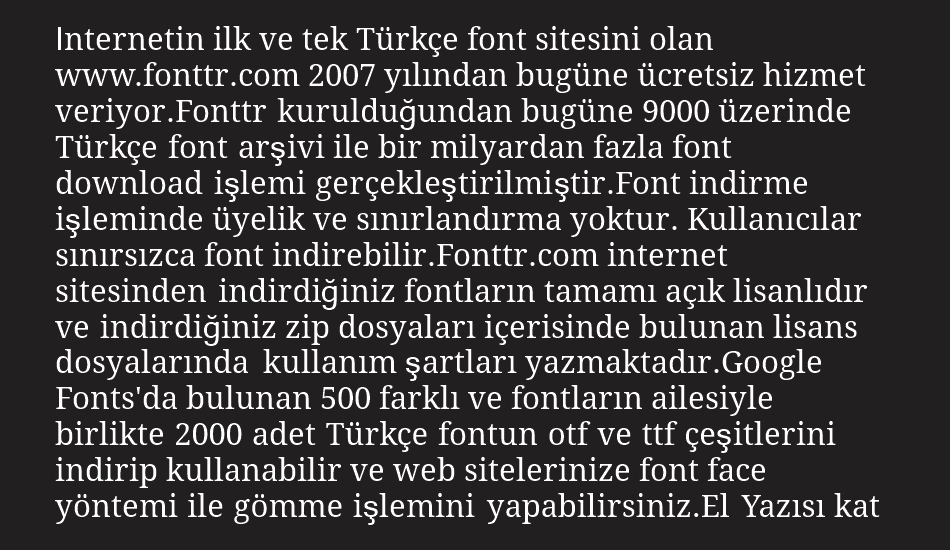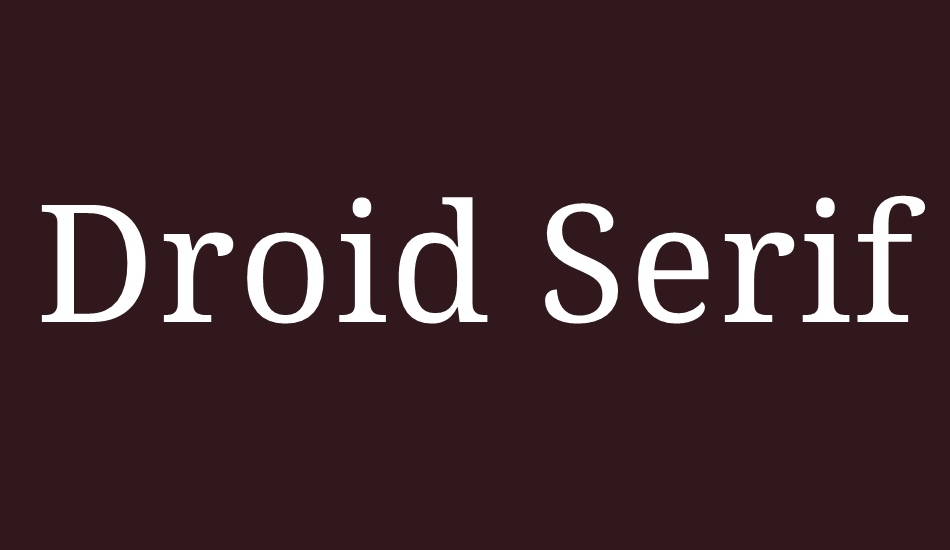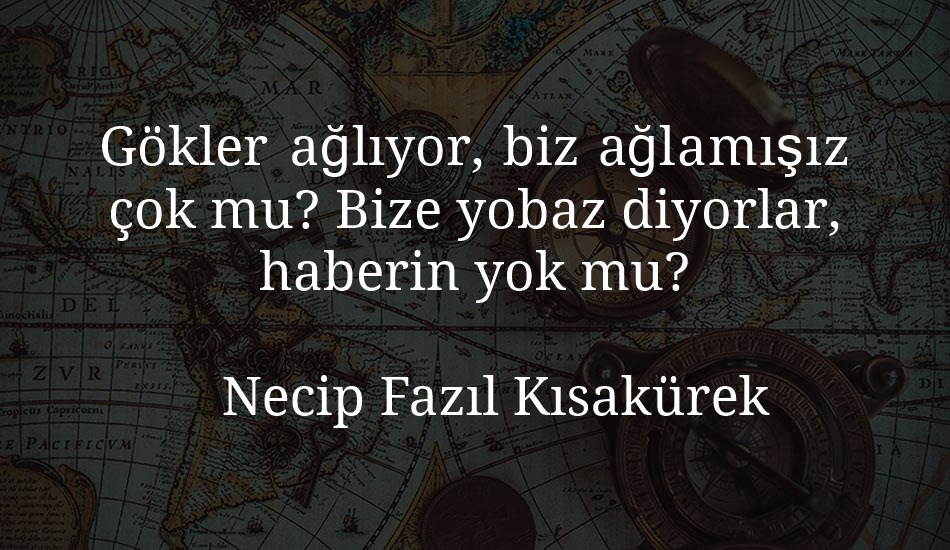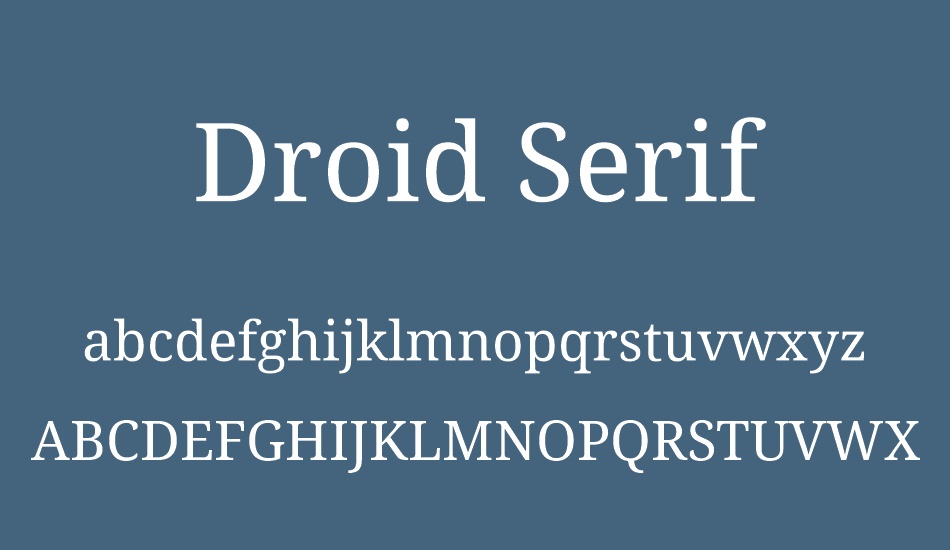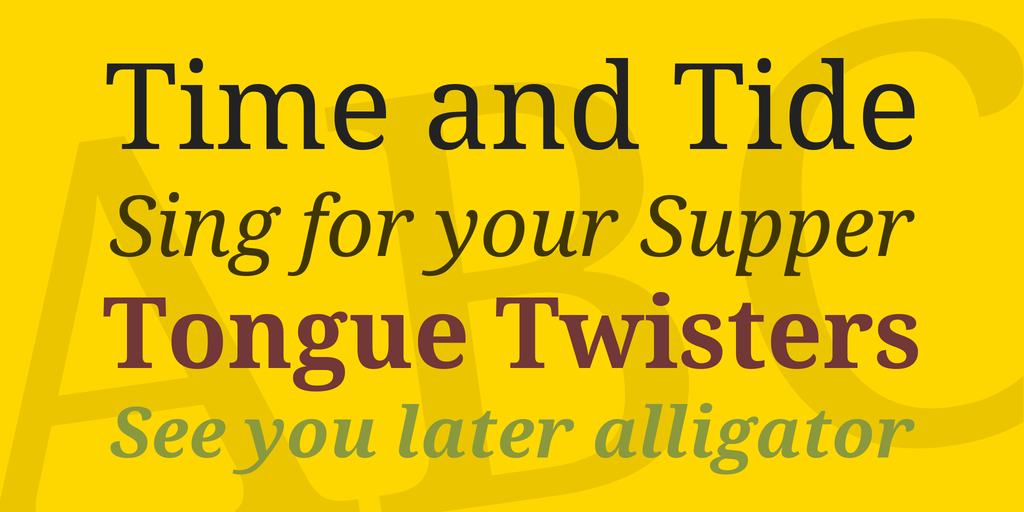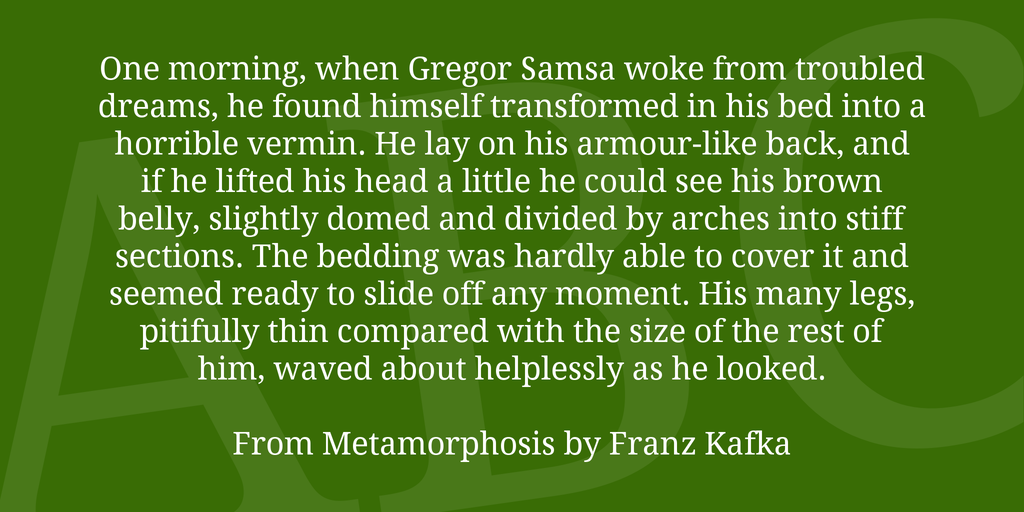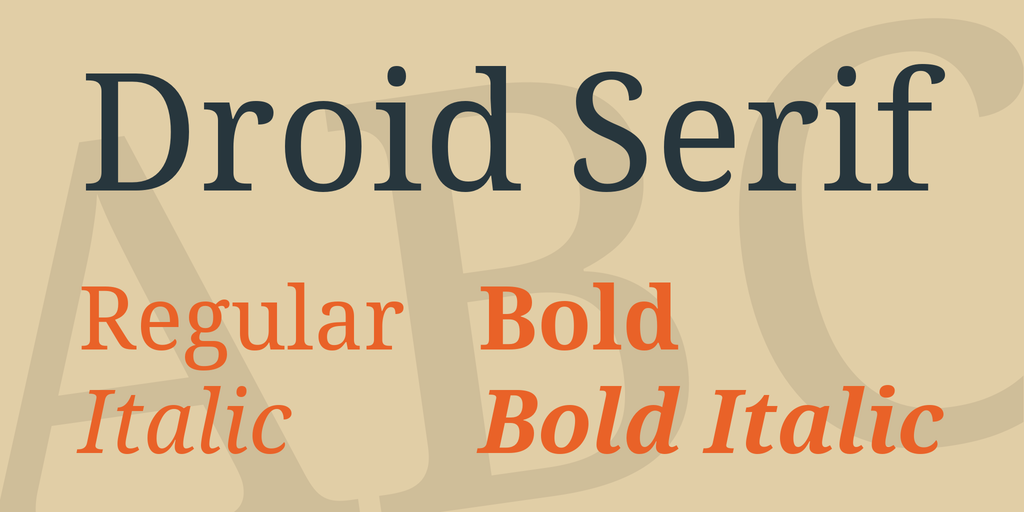
Droid Serif Font Family font
Droid Serif, ekrandaki rahat okumak için tasarlanmış çağdaş bir serif yazı tipi ailesidir. Droid Serif, küçük ekranlarda görüntülenen metin miktarını en üst düzeye çıkarmak için hafif yoğunlaştırılmıştır. Dikey stres ve açık formlar, okunabilirliğine katkıda bulunurken, orantısı ve genel tasarımı eşlik Droid Sans'ı tamamlar.